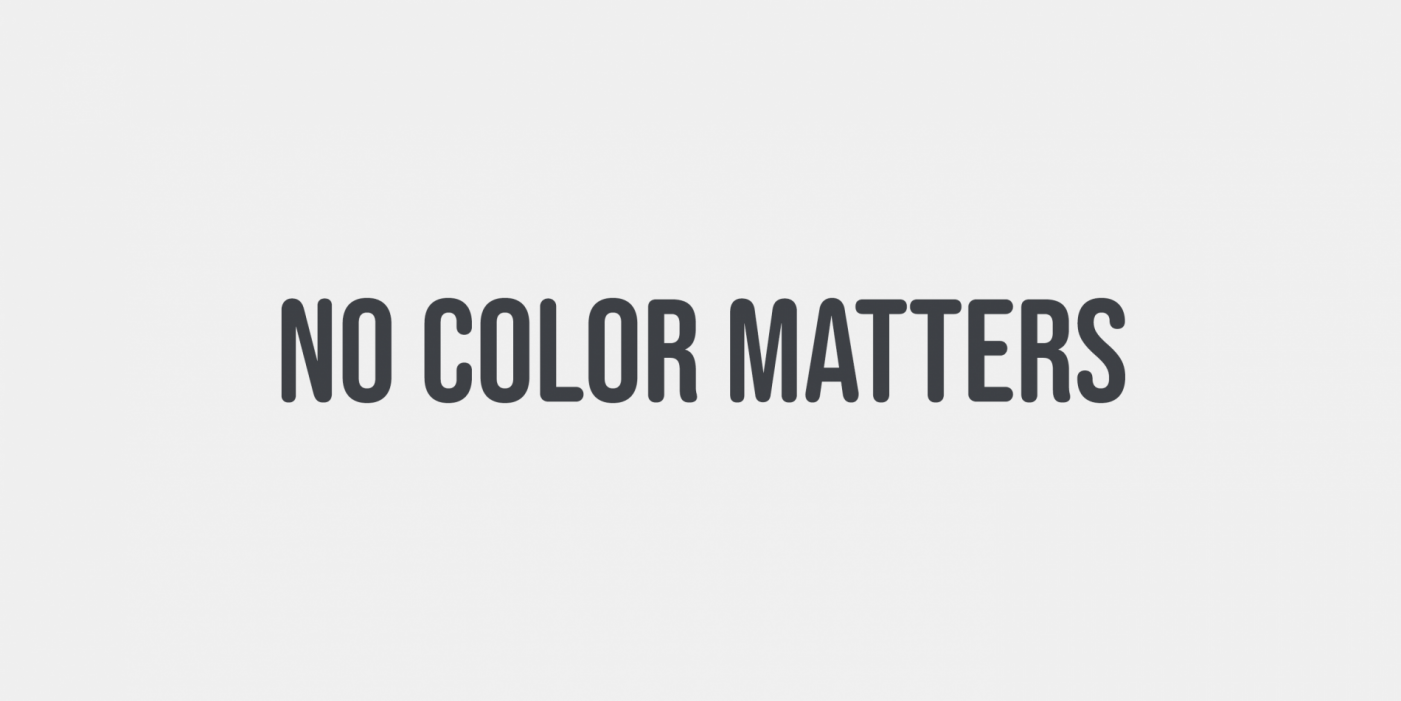
Alternativen zur Bebas Neue Rounded gesucht
ich suche eine Schriftfamilie mit runden Strichenden welche in der Grundstruktur der Bebas Neue Rounded ähnelt aber besser ausgebaut ist.
Im Grunde sollte es eine Art Proxima Soft sein, aber eben mit steilem Gerüst oder eine Knockout mit runden Strichenden, wie Ihr wollt. :-)
Hauptsache sie enthält eine fließtexttaugliche Weite inkl. Kursive und eine schön schmale Weite für Überschriften.  Spontane Ideen?
Spontan fühlte ich mich an die DIN Next Rounded erinnert, die hat aber keine Kursive. Die VAG Rounded Next vielleicht?
Dank Dir fürs Mitsuchen. Die DIN hat leider auch nicht die gewünschte schmalen Schnitte und der VAG fehlt zudem das steile Gerüst.
Wahrscheinlich nicht schmal genug??? Und die Ausbaustufe habe ich auch noch nicht ausreichend getest ...
Danke. Eigentlich gar nich so schlecht. Das R ist hübsch und das steile Gerüst und die Buchstaben-Alternativen. Allerdings fehlt ihr tatsächlich noch die zweite schmale Weite und die runden (nicht gerundeten) Strichenden. Aber als Kompromiss ginge sie vielleicht. Wird erstmal notiert.
Aber Spaß beiseite: Die geht bzgl. Gerüst genau in die gesuchte Richtung, wenn es auch gar nich sooo steil und eckig sein müsste. Allerdings fehlen hier irgendwie eine normale Weite für den Fließtext und die konsequent runden Strichenden wie bei der Proxima und Bebas:-(